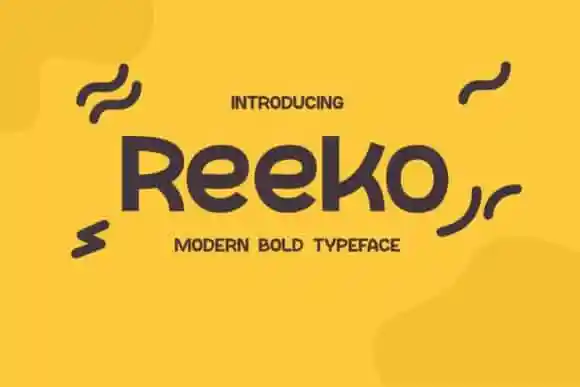
Reeko Sans Serif Font – Fonte Grátis
Reeko Sans Serif Font
Reeko Sans Serif é uma tipografia sans serif desenvolvida por typocrisy.studio que traz um toque assertivo para projetos digitais modernos e criativos. Perfeita tanto para as redes sociais quanto para trabalho de bordados, reciclagem ou qualquer outro projeto que exija um ar moderno e versátil. Suas linhas retas e sua disposição minimalista oferecem grande flexibilidade, adaptando-se a uma variedade incrível de designs. Seja você um designer de redes sociais buscando uma fonte que se destaque em seus posts ou um hobbyista criativo lançando novos trabalhos de reciclagem, Reeko Sans Serif está certamente no seu caminho.